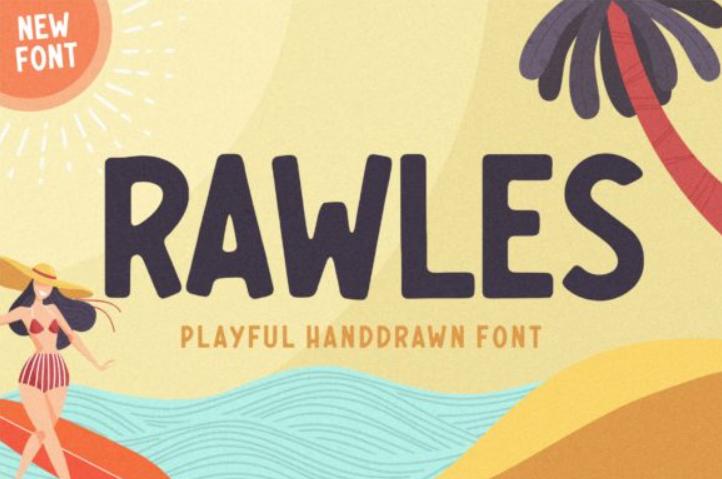
[Creativefabrica] Rawles Font (Balpirick)
Rawles - яркий и игривый дисплейный шрифт. Добавьте этот шрифт в винтажном стиле к своему творению. Независимо от темы, этот шрифт станет невероятным активом в вашей библиотеке шрифтов, так как он может улучшить любое творение.